Las tipografías es un recurso indispensable para el diseñador, ya que conseguiremos darle una personalidad única a nuestro proyecto eligiendo la tipografía que mejor venga para el tema que estemos tratando, además de facilitar la lectura al usuario. A lo largo de los años la tipografía ha cambiado y ha evolucionado, para dar lugar a diversas variantes. En este artículo os mostraré 10 de las mejores tipografías hechas a mano que existen hoy en día, para que podáis usarlas en vuestros sitios web y creéis un sitio único y lleno de personalidad. Allá vamos:
15 Handwritten Fonts – Font Pack
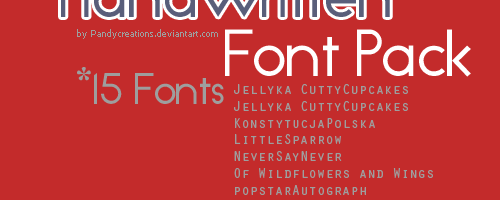
Just Nate – Handwritten Font
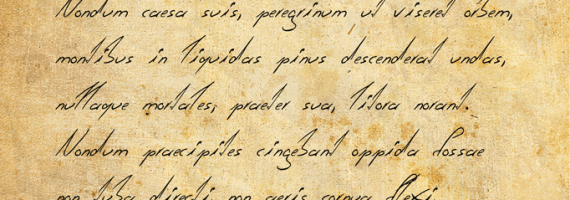
Jenna Sue – A handwritten font
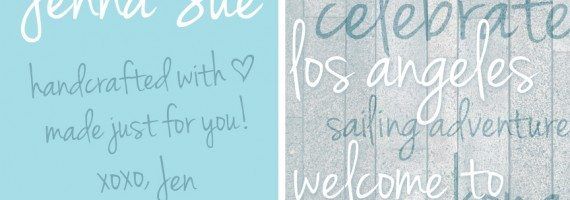
Font – Shark HandWritten ABC
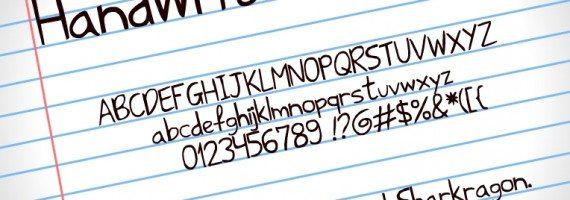
Handwritten fonts collected by MissiDesigner
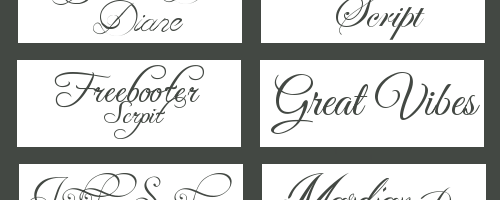
HandyHandy Font
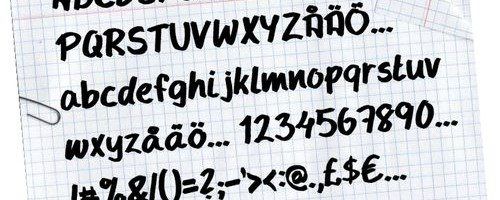
Nathaniel Font
LT Chickenhawk Font
Celeste Hand Font
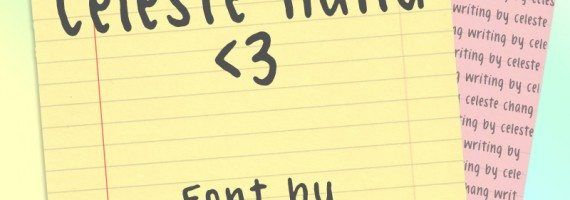
Hacjiuza Dirty – Free Font